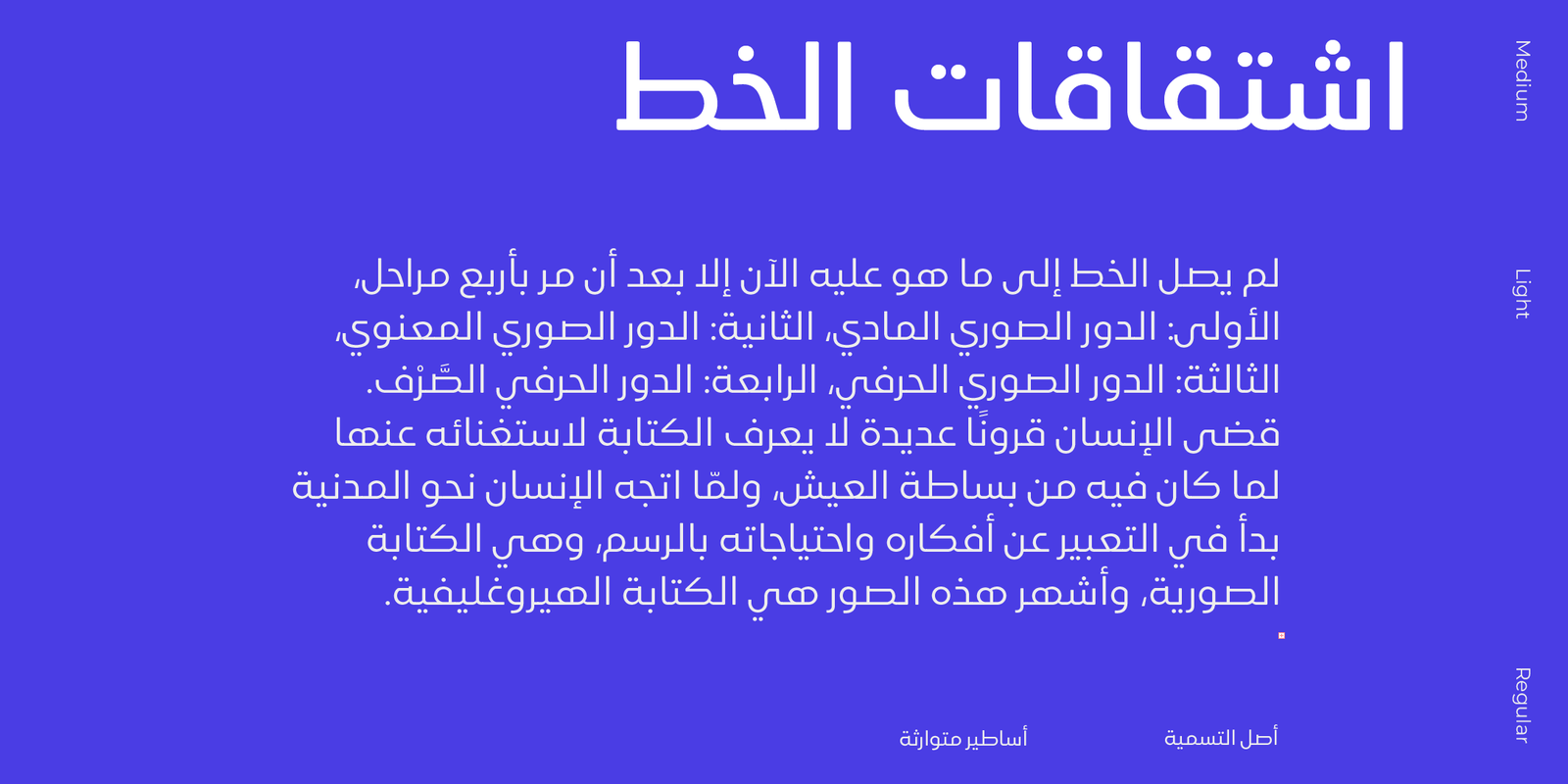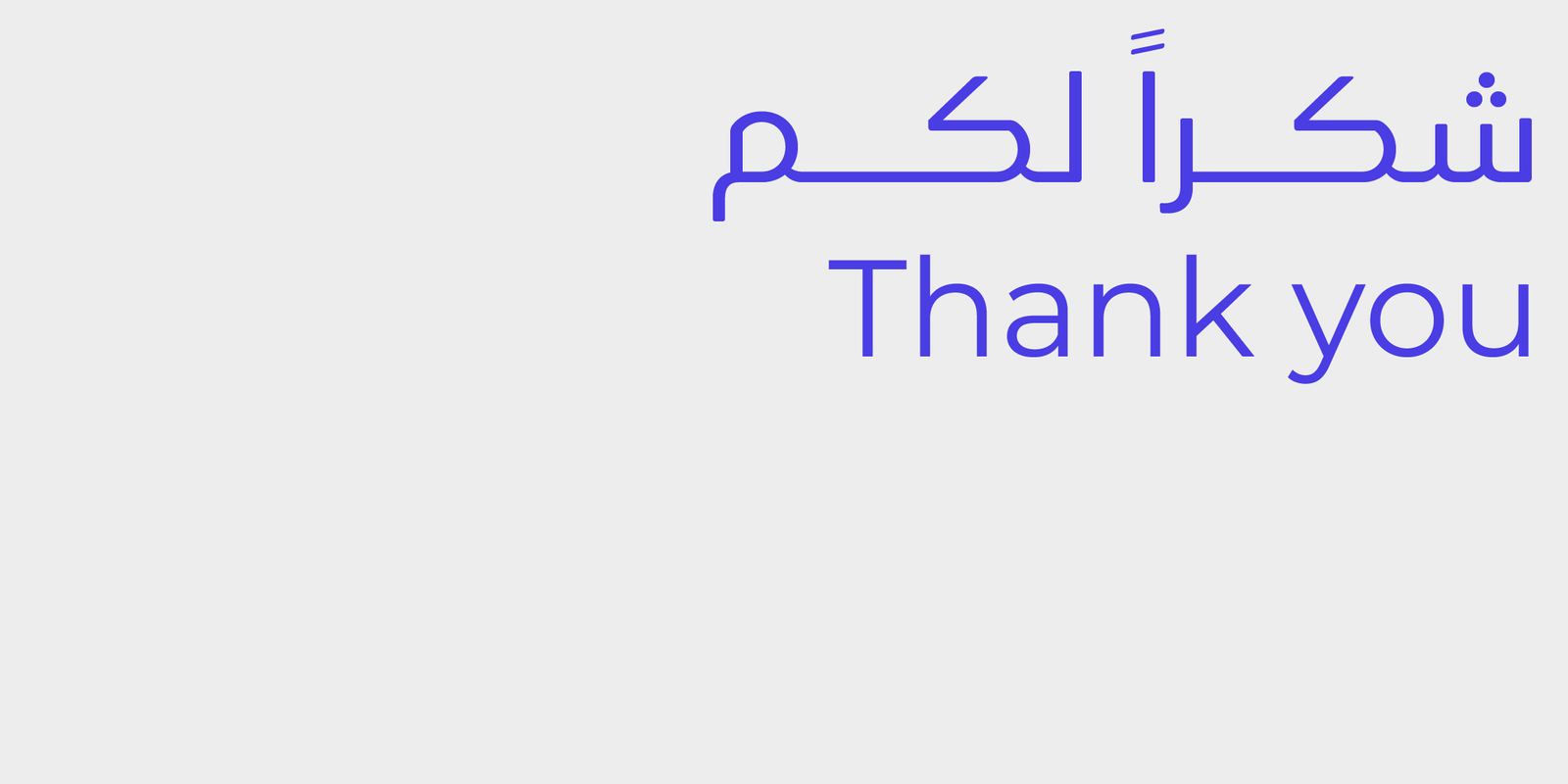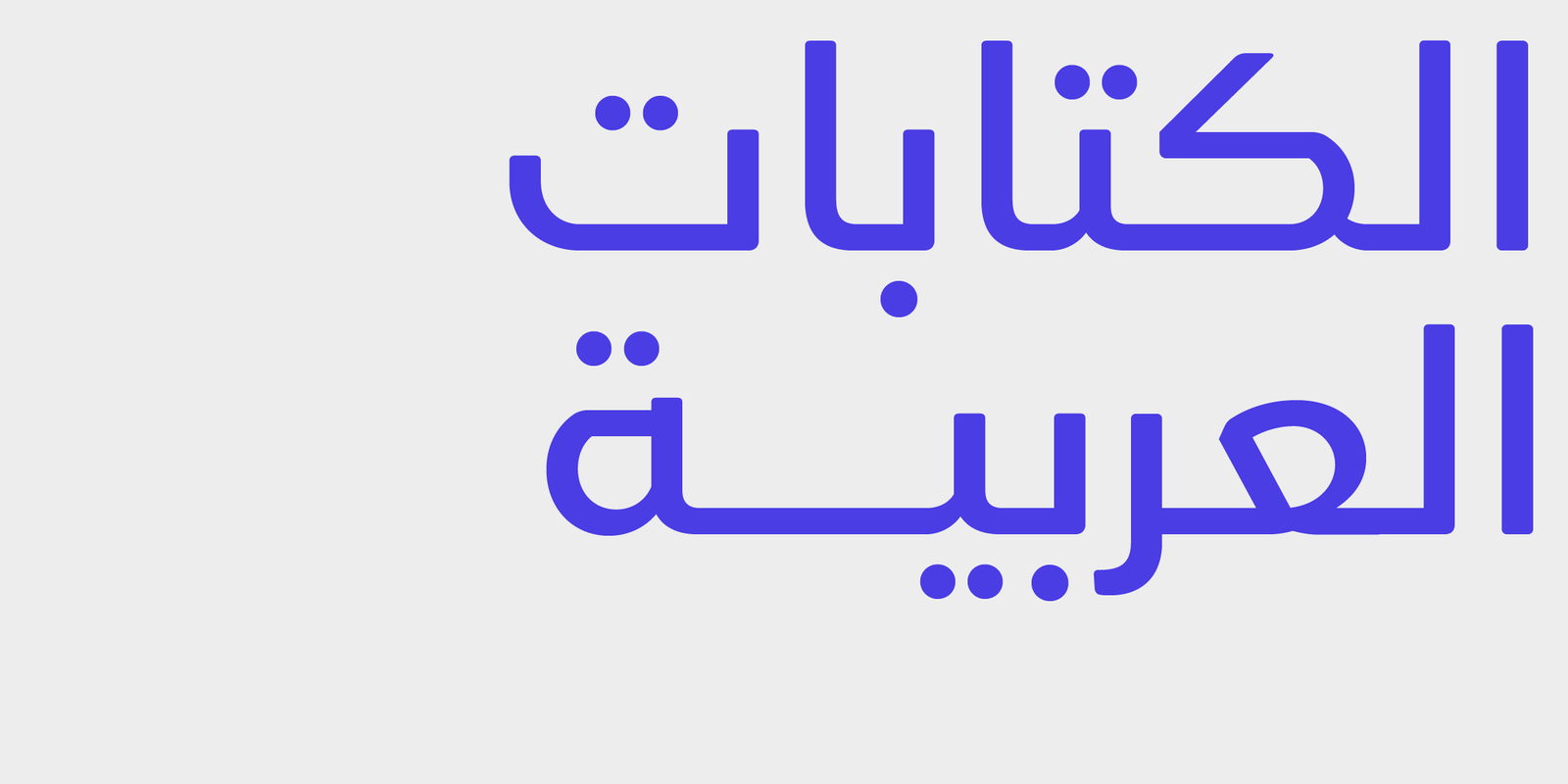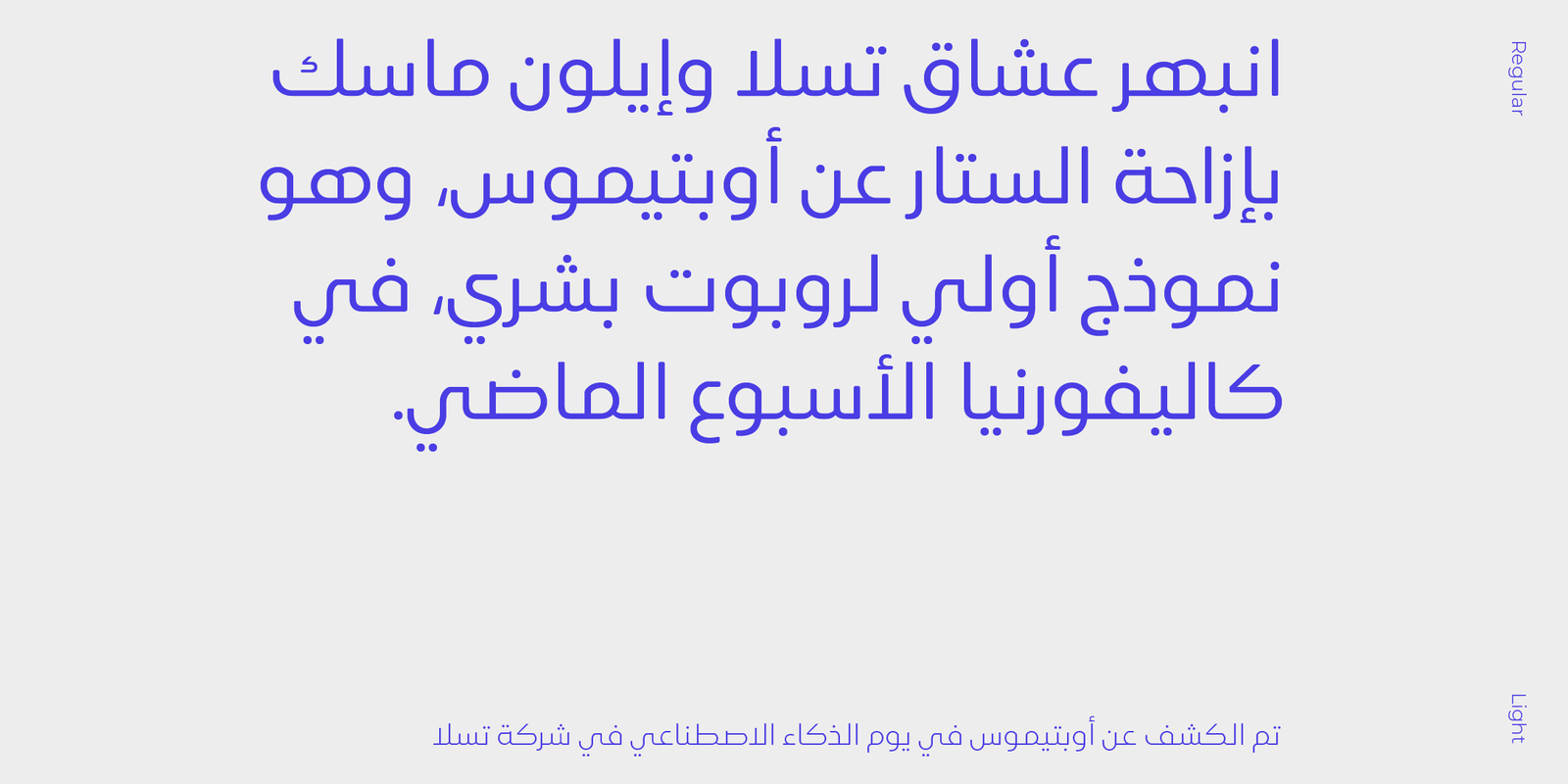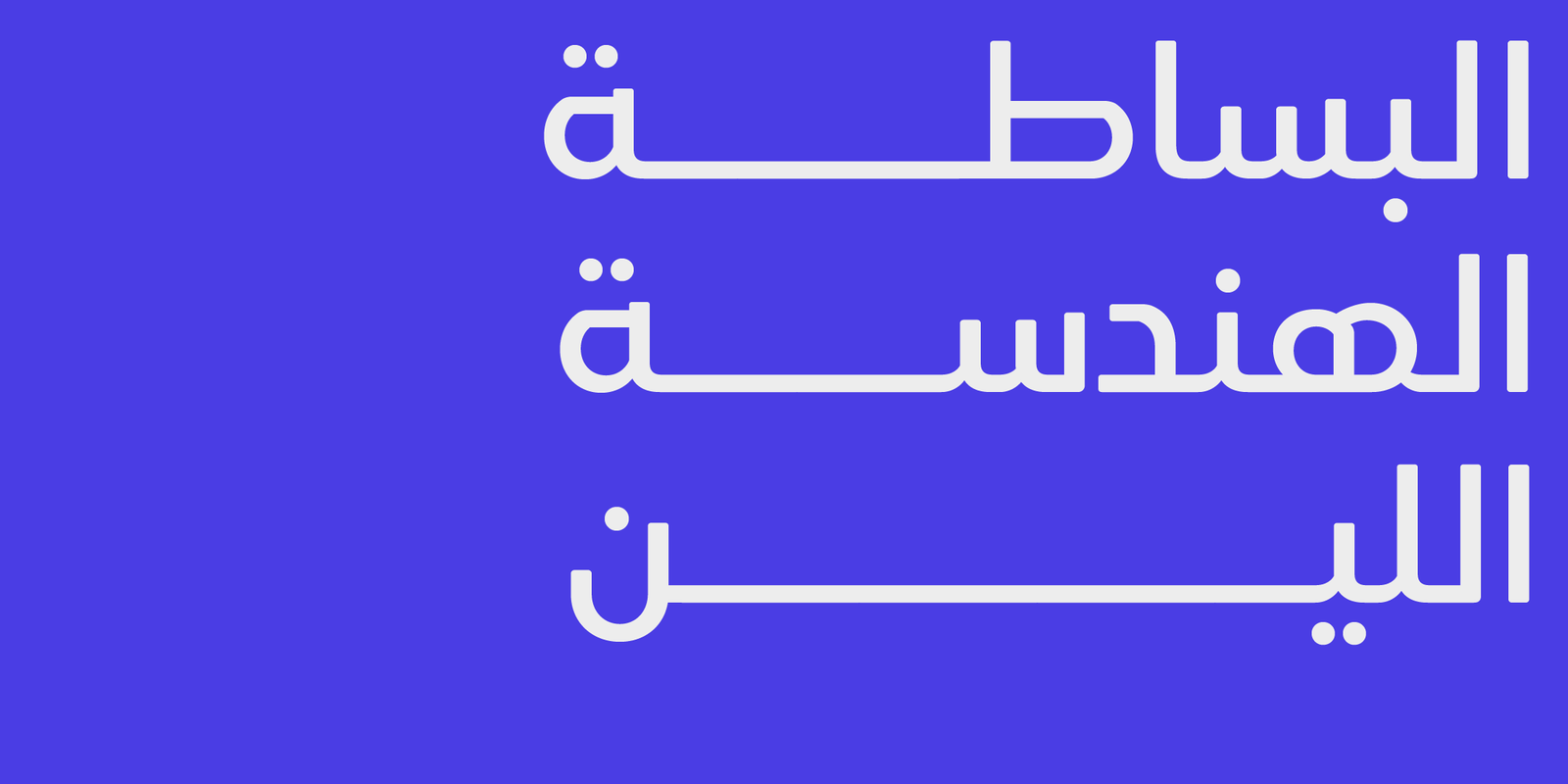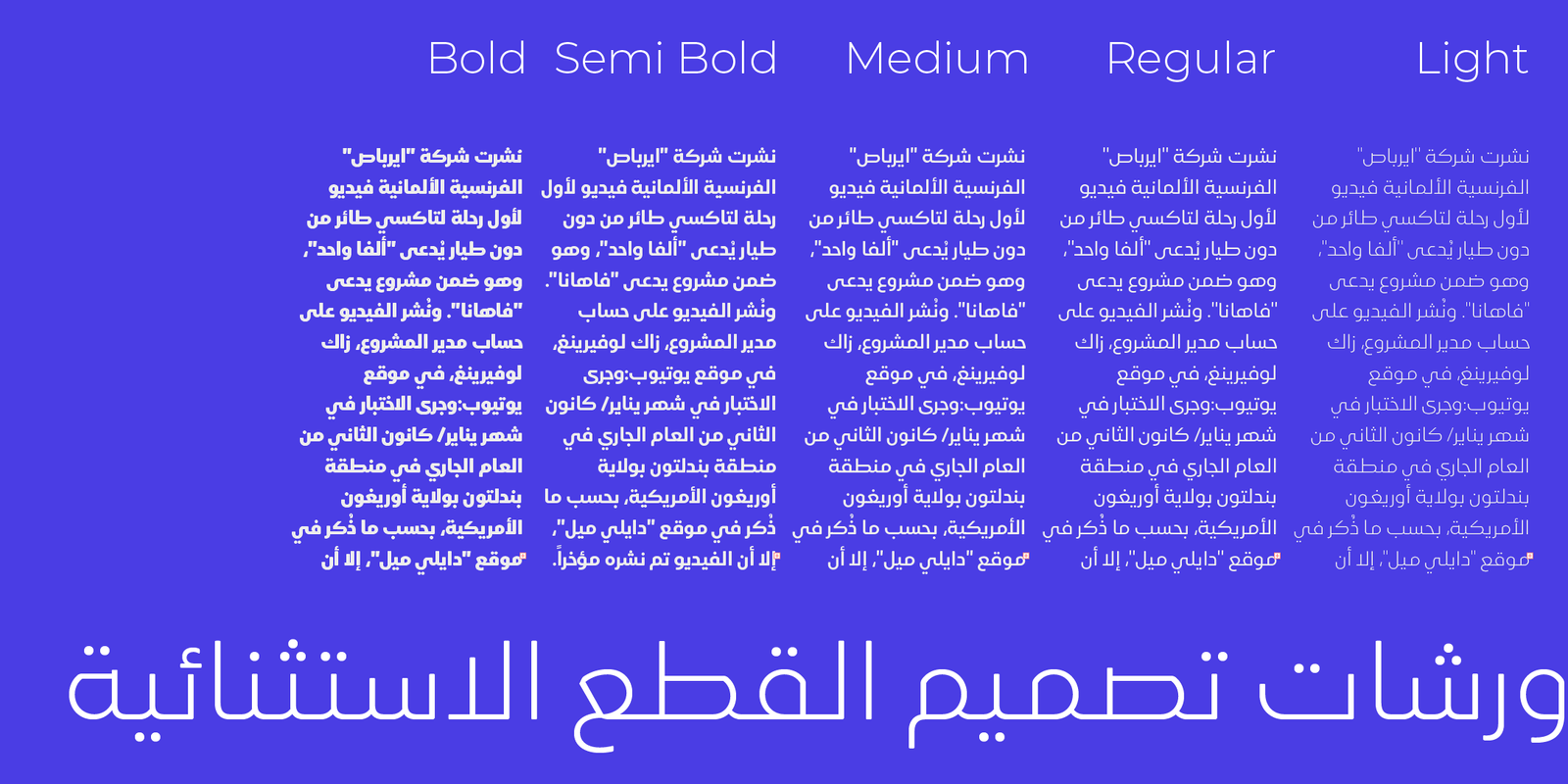
Ruaq Arabic typeface – خط رواق
رواق خط عربي أنيق وعصري. يتميز هذا الخط الهندسي بحواف ناعمة وخطوط بسيطة تمنحه مظهرًا بسيطًا ونظيفًا.
مع خمسة أوزان مختلفة تتراوح من الخفيف إلى العريض، يعد رواق مرنًا بما يكفي ليناسب أي مشروع ويمكنه التعبير
عن مجموعة متنوعة من الحالات المزاجية، من المرح إلى الاحترافية.